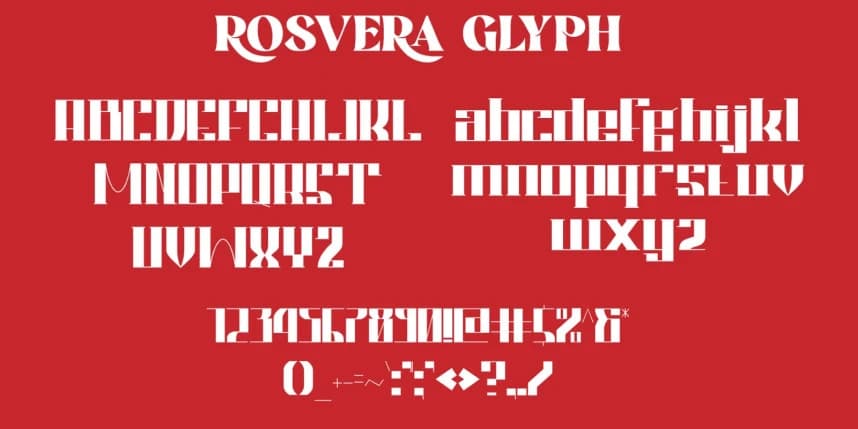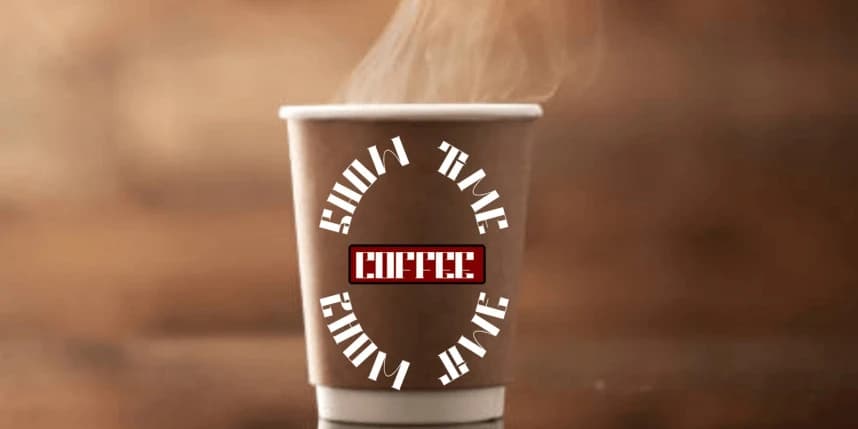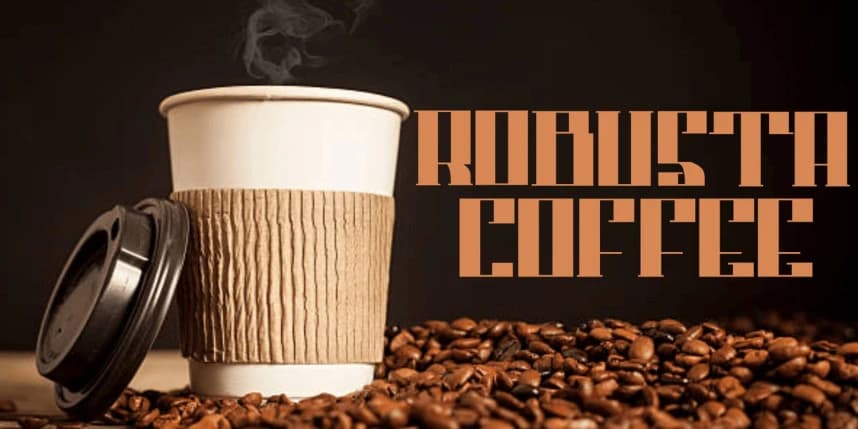
Rosvera Font
Rosvera Font, zarif bir serif gösterim yazı tipidir ve lüks, modern stil ve zamansız zarafeti bir araya getirir. Sanatsal harf biçimlerine ve güçlü serif detaylarına sahip olan bu yazı tipi, markalaşma, logolar, başlıklar, moda projeleri ve kozmetik için mükemmeldir.
Rosvera Font, lüks, modern stil ve zamansız zarafeti bir araya getiren zarif bir serif gösterim yazı tipidir. Sanatsal harf biçimleri ve güçlü serif detaylarıyla, bu yazı tipi marka oluşturma, logolar, başlıklar, moda projeleri ve kozmetik için mükemmeldir.